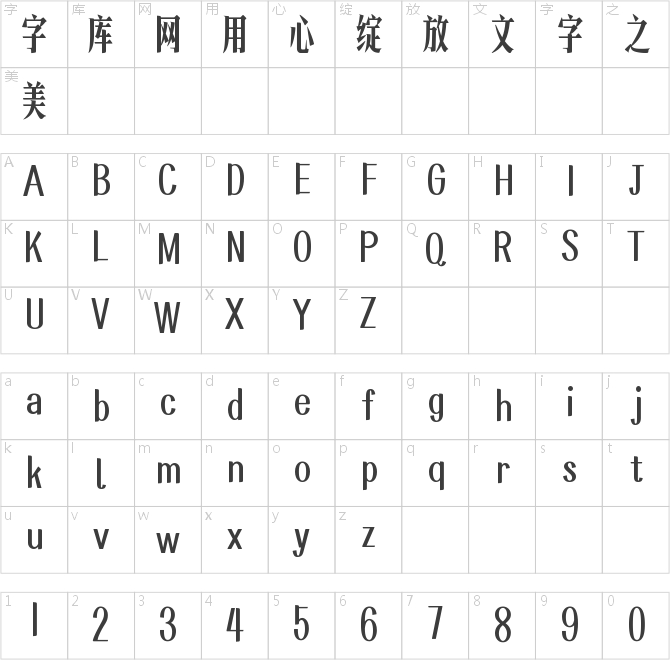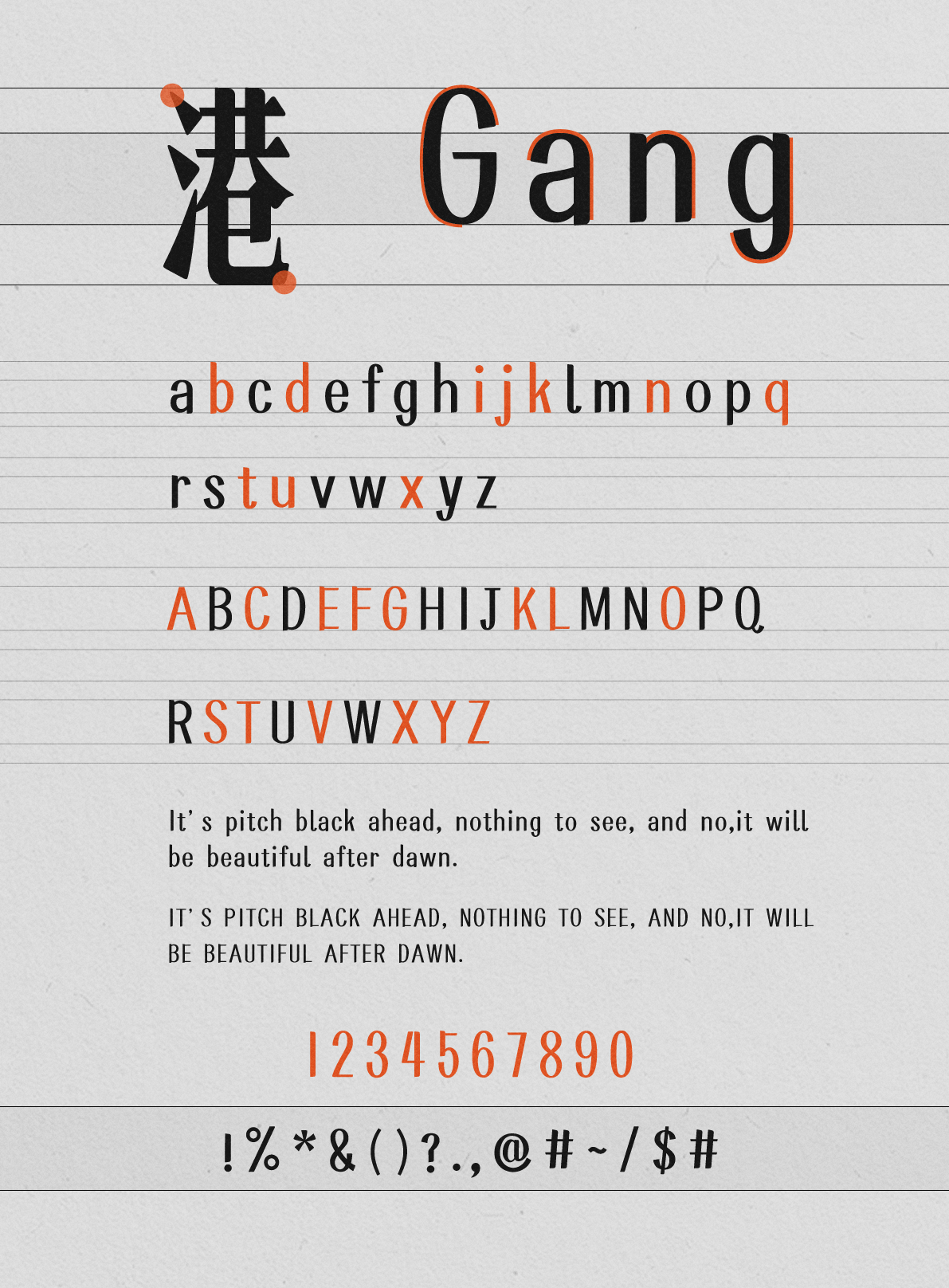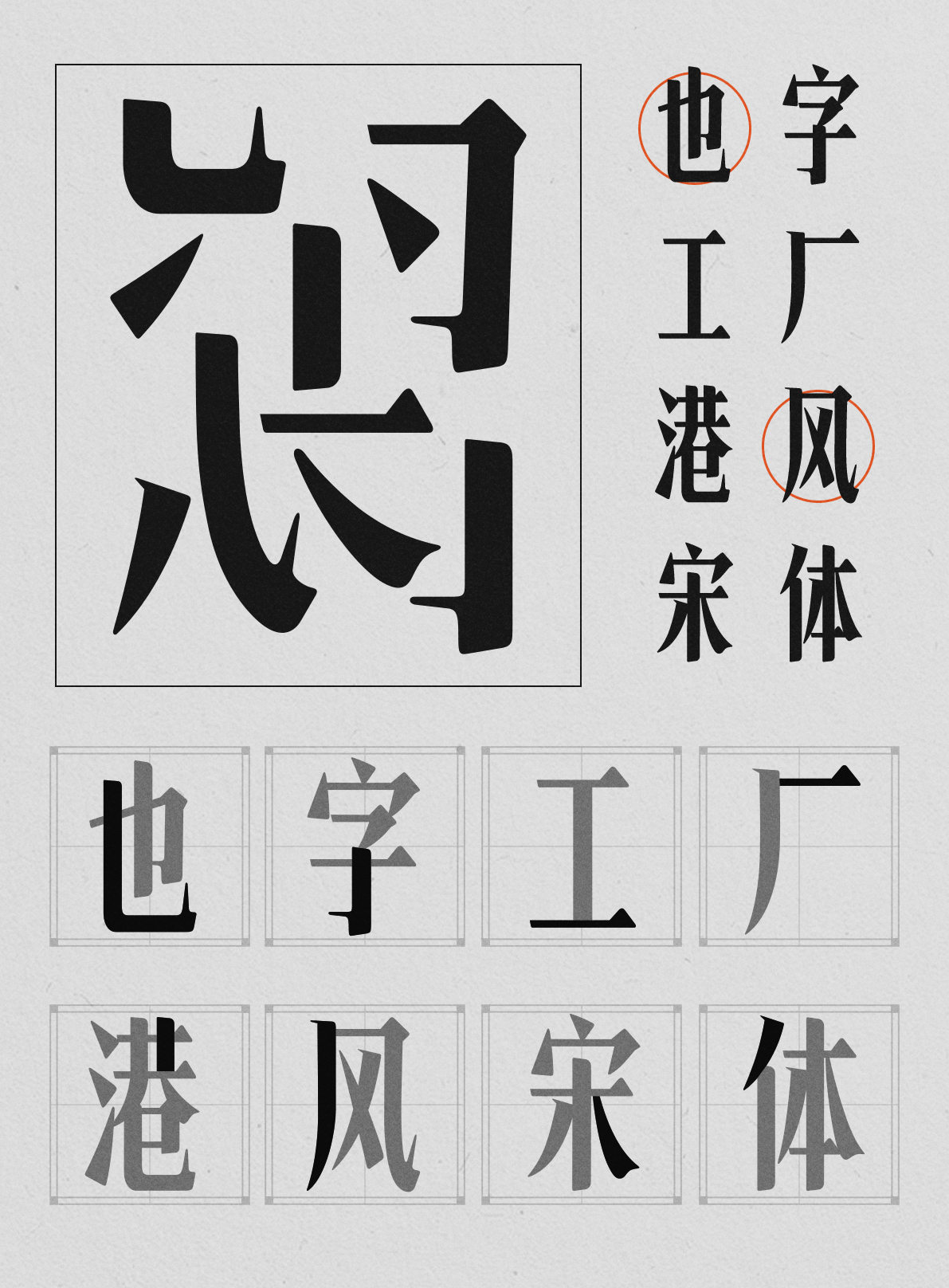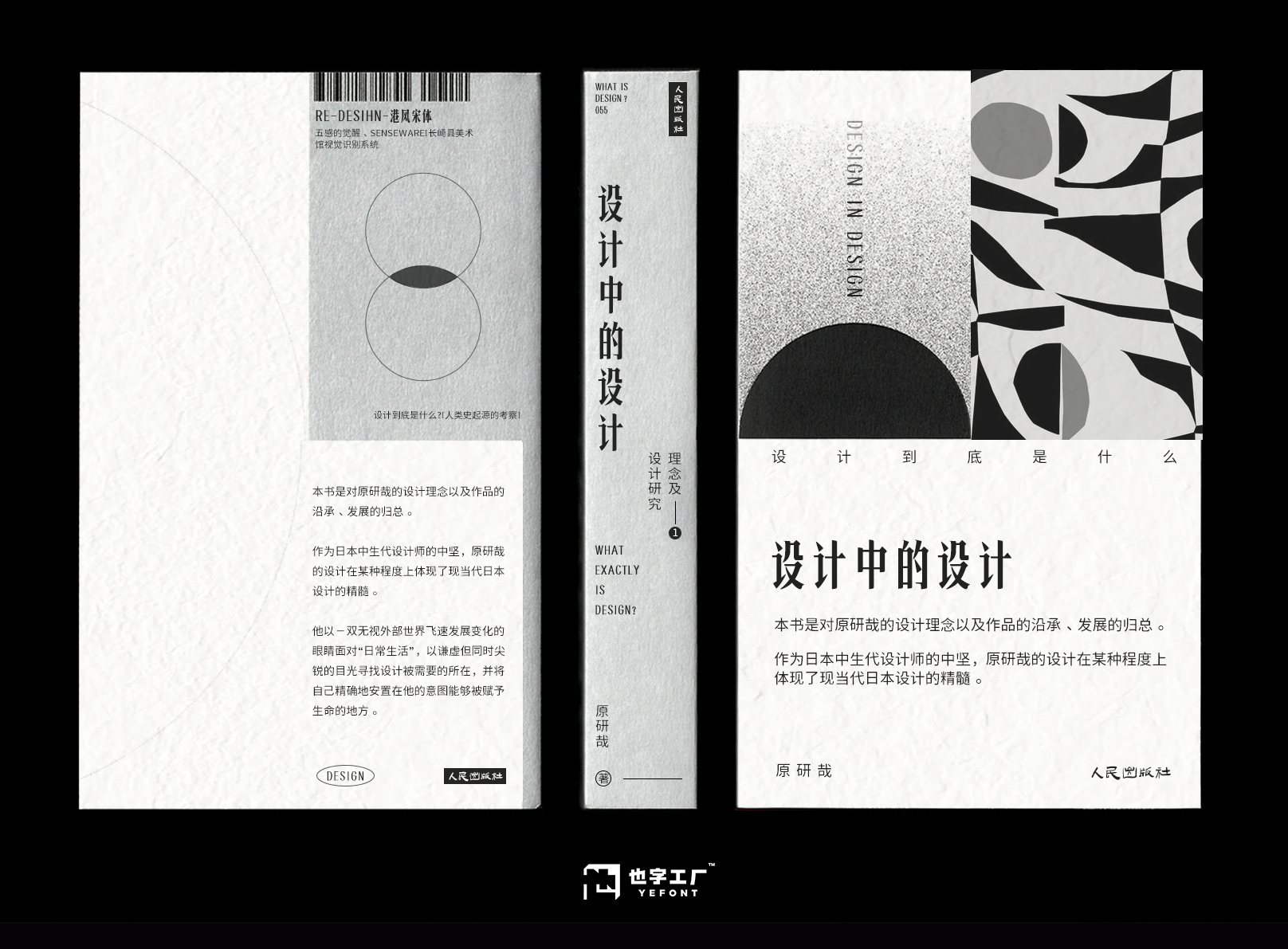
港風(fēng)宋體:根植于香港文化的反哺情懷
香港這座城市,它的獨特性與生俱來。在歷史的長河中,香港在東西方文化交匯中獨樹一幟,既有民族性又有現(xiàn)代性的文化互滲與共融。對傳統(tǒng)價值觀、文化傳承有著守舊而老派的認(rèn)知和態(tài)度,但同時也不乏前衛(wèi)、先鋒的思想和行為。這種傳統(tǒng)與前衛(wèi)的結(jié)合,成為香港獨特的城市氣質(zhì)。
在香港,你可以看到高樓林立的城市景觀,也可以看到洋溢著濃郁歷史氣息的街頭巷尾。民間關(guān)系縱橫交錯,各階層之間存在著深深的裂痕。然而,這樣的混亂在香港卻可以達(dá)到一種平衡,如同一幅有限而豐富的畫卷,將人們的不同意識形態(tài)和信仰融合,將過去和現(xiàn)在交織,形成了別致的城市面貌。就是這樣的香港,孕育出讓世界津津樂道的在地文化,從電影、文學(xué)、藝術(shù)、音樂劃分出不同維度的時代隱喻齊頭并進(jìn),成為幾代人心目中如數(shù)家珍的經(jīng)典記憶。
作為一家具有獨創(chuàng)性的字體設(shè)計品牌,也字工廠常年致力于探索和挖掘字體藝術(shù)文化領(lǐng)域的潛在價值和無限可能。我們一直密切關(guān)注著與字體緊密相關(guān)的藝文產(chǎn)業(yè),以提供更具創(chuàng)意和實用價值的字體設(shè)計服務(wù)。鑒于此,也字工廠即將面向市場首推新品字體——「港風(fēng)宋體」
在字體設(shè)計的過程中,也字工廠團(tuán)隊深刻意識到在選擇港風(fēng)宋體的定位時,「港風(fēng)宋體」作為一種具有城市氣質(zhì)的字體,它應(yīng)該能夠體現(xiàn)出這座城市的文化特色、藝術(shù)底蘊(yùn)和氛圍。所以我們從香港電影中汲取了靈感,以電影海報的字體作為發(fā)力點,我們投入了大量的時間、精力進(jìn)行素材的收集與整合,最終確定我們要呈現(xiàn)的字體特征,「港風(fēng)宋體」具有瘦長的外形特點,筆畫纖細(xì),橫豎粗細(xì)對比明顯。這種設(shè)計風(fēng)格正是迎合了港風(fēng)文化所需要的特性。
特點&應(yīng)用:出于對香港文化的喜愛和尊重,也字工廠希望通過「港風(fēng)宋體」的設(shè)計作品來傳達(dá)出這種情感,并反哺香港文化所帶來的價值認(rèn)同和審美共通。在市場上,雖然類似港風(fēng)的黑體字已經(jīng)存在,但與之形成鮮明對比的是「港風(fēng)宋體」的筆觸輕盈,讓人從不同的字體的設(shè)計差異中領(lǐng)略到香港在不同時空下那份若有若無的藝文氣息。
港風(fēng)宋體是一款經(jīng)過反復(fù)打磨和調(diào)整的美術(shù)宋體,設(shè)計精致且講究。作為一種美術(shù)宋體,港風(fēng)宋體可廣泛應(yīng)用于海報、招牌、站牌、文創(chuàng)等場景。其設(shè)計方向的獨特之處,使得「港風(fēng)宋體」在文化符號的呈現(xiàn)方面擁有強(qiáng)大的表現(xiàn)力。用「港風(fēng)宋體」制作電影海報,可以更加貼近香港電影的特點,展現(xiàn)出香港電影的獨特魅力;用「港風(fēng)宋體」制作招牌,可以讓顧客更直接地感受到香港文化的氛圍;用「港風(fēng)宋體」制作文創(chuàng)產(chǎn)品,可以為香港的文化傳承增添一道亮麗的風(fēng)景線。
我們希望它能夠成為廣大設(shè)計師們在海報、標(biāo)志、出版物甚至裝飾設(shè)計中的得力助手。我們堅信,港風(fēng)宋體不僅僅是一種字體,它更代表著香港的多元魅力和文化內(nèi)涵。讓我們一起期待「港風(fēng)宋體」的表現(xiàn)與使用,讓它成為一個新時代的文化符號